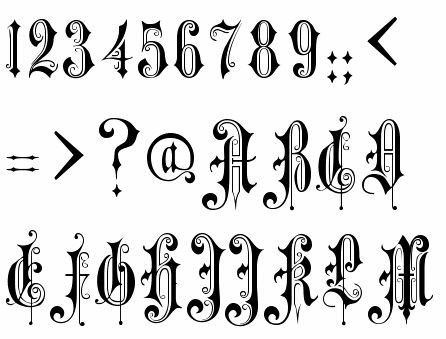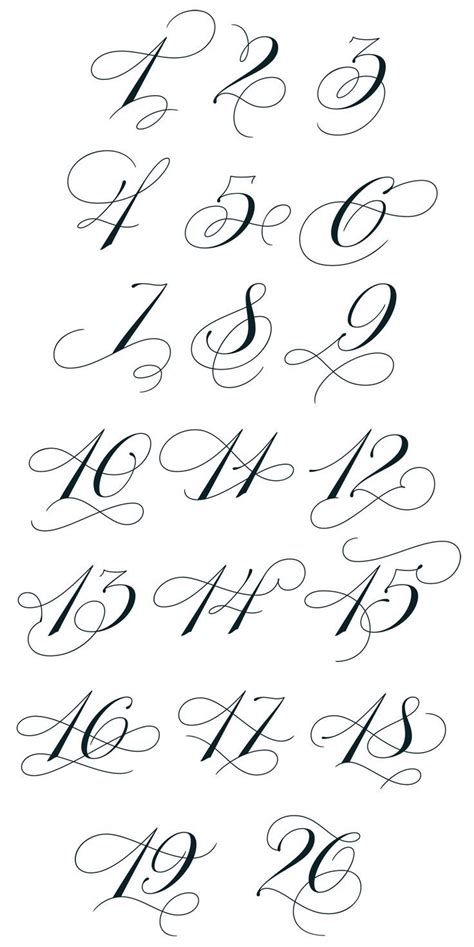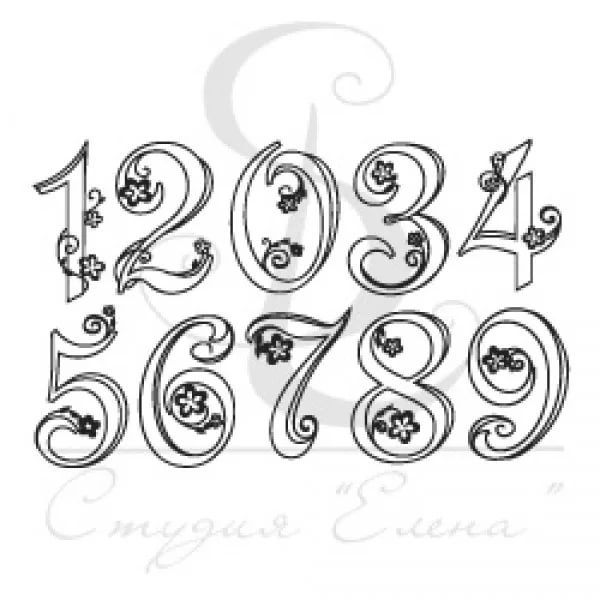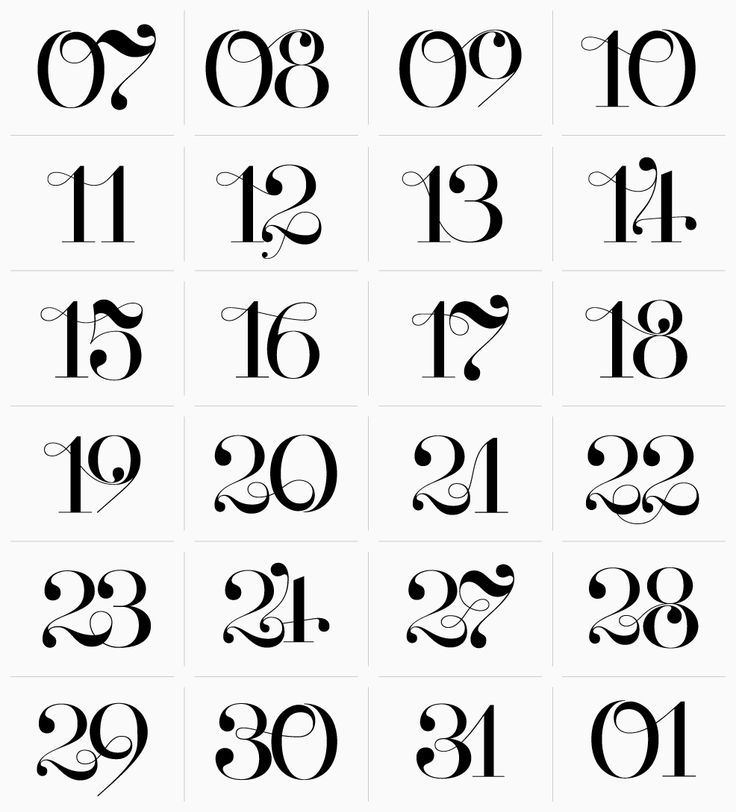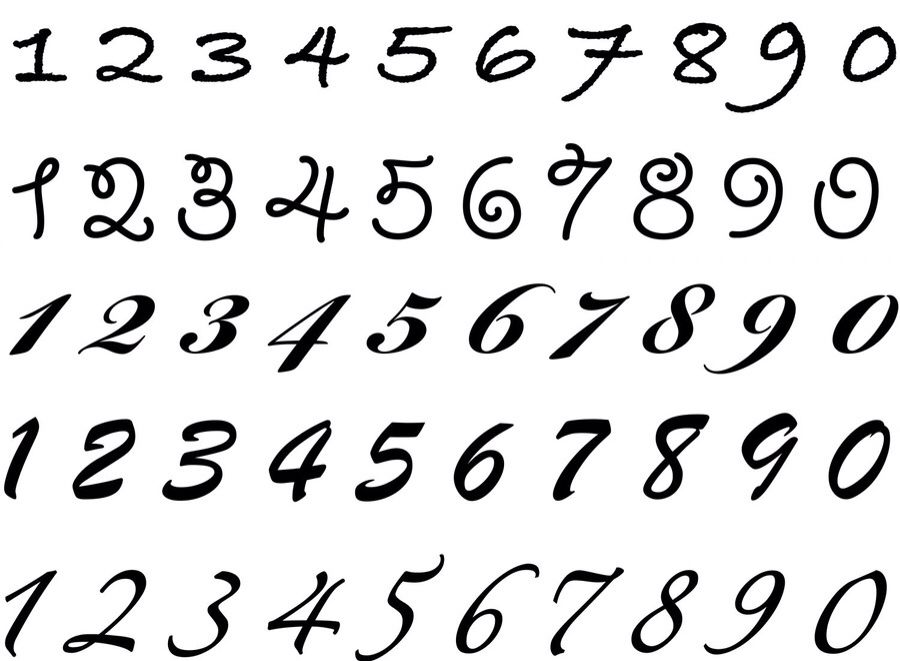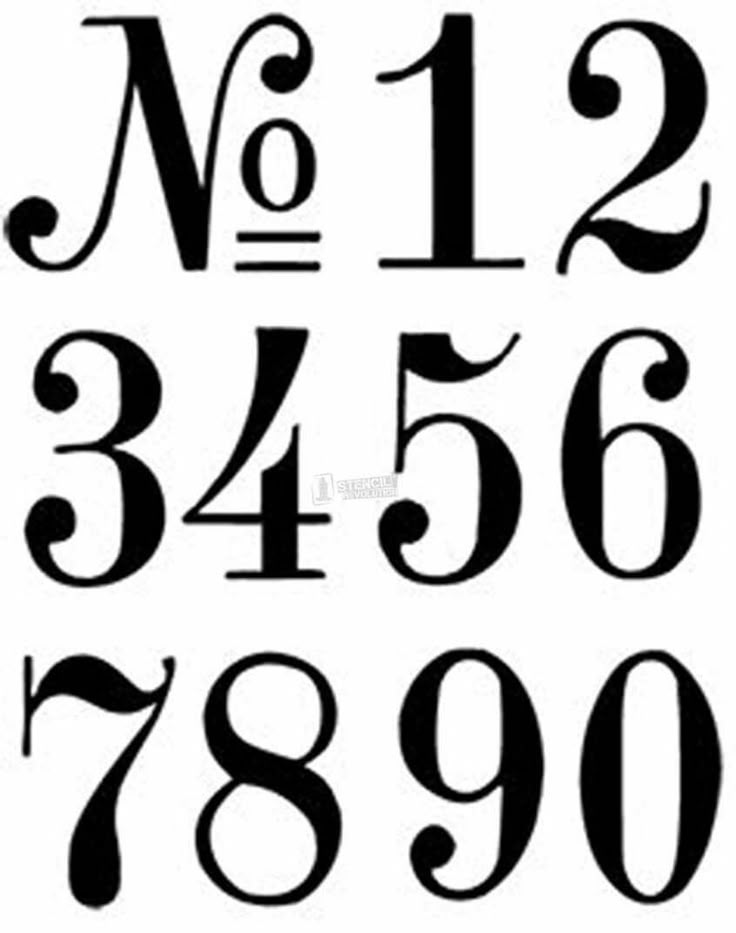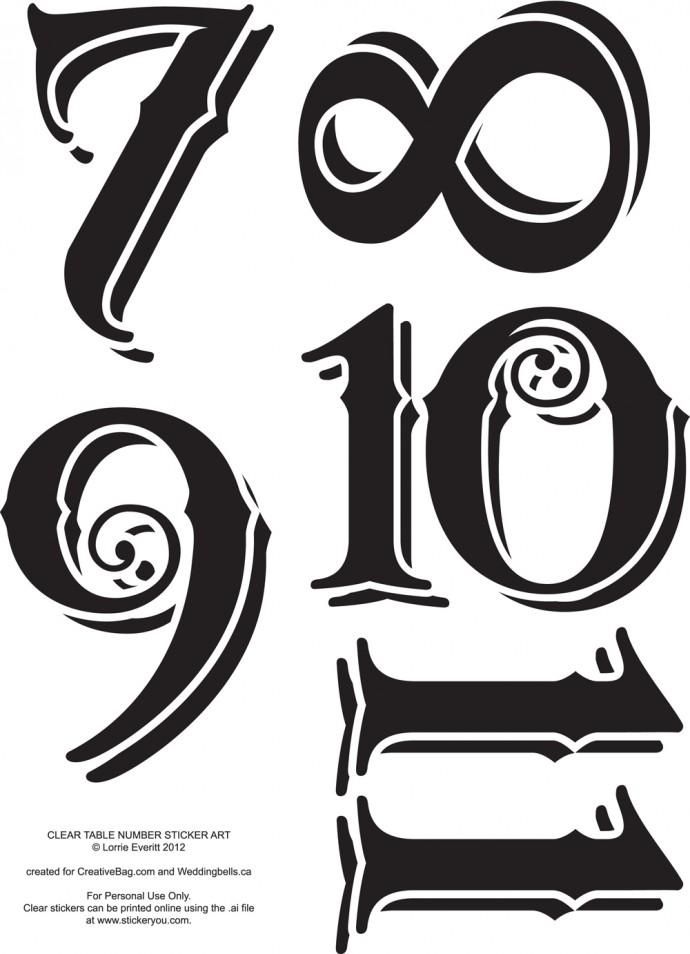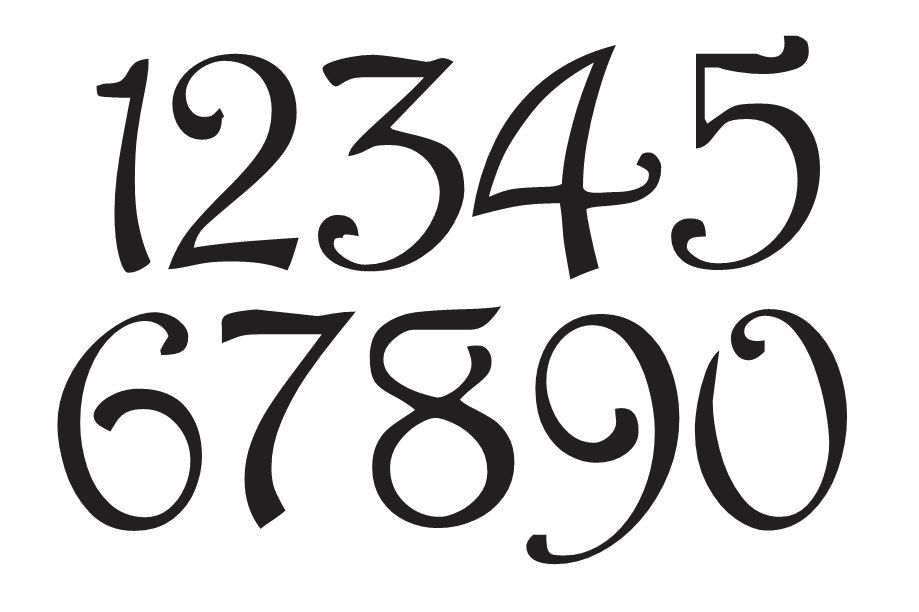
Сегодня я завершу рассказ о фичах. Этот совет — про цифры, альтернативные знаки и стилистические сеты.
В прошлом совете я разбирала принцип позиционирования и замены знаков. И цифры, и альтернативные знаки, и стилистические сеты действуют по принципу замены знаков. С такими фичами мы можем менять форму знаков или цифр.
Цифры
Во многих шрифтах есть несколько наборов цифр для разных задач: табличные (моноширинные), минускульные (старостильные), маюскульные (основные), минускульные табличные.
Обычно самые стандартные цифры — маюскульные, то есть размером с прописные знаки. Их можно заменить на табличные или моноширинные — рисунок останется тем же, но выравнивается ширина каждой цифры. Табличные цифры идеальны для таблиц — при большом количестве чисел искать нужное число удобнее, когда все цифры стоят в ряд друг под другом:
Если цифр в таблице много, и часто нужно находить определённые числа, то моноширинные табличные цифры подойдут лучше всего.
Минускульные цифры чаще всего встречаются в антиквах, потому что они хорошо смотрятся в строке в большом наборе текста.
Минускульные цифры ровняются по высоте строчных знаков и имеют выносные элементы. Шрифт Бюросериф
Но в гротесках они тоже часто есть, и иногда они могут играть красивую завлекающую роль:
Обложки журнала «Московское наследие» 2013 года. Минускульные цифры в заголовках набраны шрифтом Цирцея
Минускульные цифры тоже могут быть моноширинными, если такая фича доступна в шрифте.
В Цирцее есть и моноширинные минускульные цифры
Альтернативные знаки
Альтернативные знаки — это другой рисунок буквы. Обычно нужны для достижения определённого визуального эффекта.
Альтернативные знаки условно делятся на контекстные и стилистические. Контекстные альтернативы работают в неудачных соединениях букв для лучшей считываемости.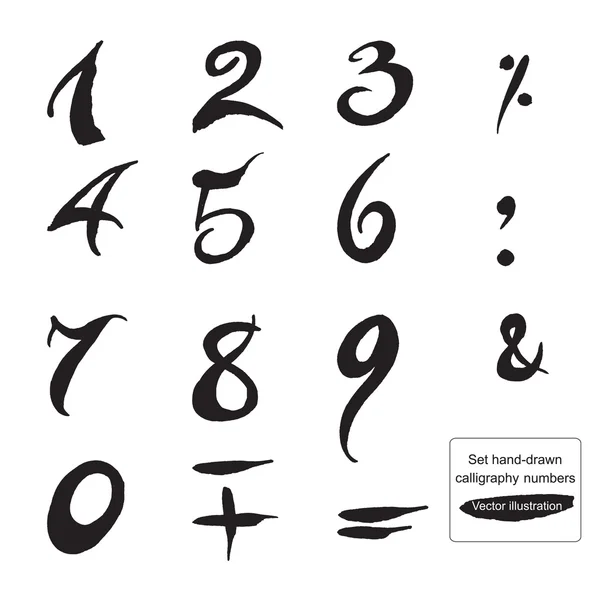
Слева двучастные «a» и «g» — состоящие из двух частей. Эти же буквы, но одночастные — стилистические альтернативные знаки. Шрифт Искра
Альтернативные знаки хорошо работают в разных акцидентных шрифтах.
Шрифт Интерлок компании «Хаус Индастрис». Его принцип схож с вязью, где каждый глиф подстраивается в ряд к другим. Глифы работают по принципу лигатур, но являются при этом альтернативными знаками. На сайте можно тестировать набор и смотреть, как ведут себя буквы. Как жаль, что нет кириллицы
Также в альтернативные знаки входят и росчерки — каллиграфические элементы в глифе.
В одном из моих любимых шрифтов Амальта красивые начальные и концевые росчерки
Стилистические сеты
Стилистические сеты — это продуманные шрифтовым дизайнером готовые наборы альтернативных знаков для достижения определённого эффекта.
Например, в шрифте Цирцея есть целых 11 стилистических сетов. В каждом из них определённые глифы заменяются на альтернативные.
Стилистический сет № 1 в Цирцее. Подробнее о стилистических сетах и остальных фичах шрифта можно прочитать в ЖЖ шрифтовой компании «Паратайп». Картинка оттуда же
Я советую обращать внимание на такие сеты, потому что они здорово могут украсить и оживить набор.
Иногда стилистические сеты сделаны специально, если пользователю понадобится добавить определённый характер в набор. Например, исторический.
У шрифта Казимир компании «Тайп тудей» есть стилистический сет под названием Irregular. У него «состаренные» знаки, которые хорошо работают в акциденции.
Картинка из ПДФ шрифта с сайта компании
Фичи — это не просто дополнительные плюшки к шрифту, а инструмент, которым можно и нужно пользоваться по необходимости. Обычно фичи показаны сразу на странице шрифта. На некоторых сайтах, например, на сайте Майфонтс, можно настроить поиск по нужным фичам. Рекомендую изучать набор фич в шрифте прежде, чем покупать шрифт.
Шрифты
Определение шрифтов, которые применяются для элементов формул.
Доступ к этой команде
Последовательно выберите команды Формат — Шрифты.
Шрифты формул
Можно определить шрифты для таких элементов формул, как переменные, функции, числа и вставляемый текст.
В списках диалогового окна Шрифт для всех элементов отображается шрифт, заданный по умолчанию. Чтобы изменить шрифт, нажмите кнопку Изменить и выберите тип элементов. Отображается новое диалоговое окно.
Выберите необходимый шрифт и установите требуемые атрибуты, а затем нажмите кнопку OK. Чтобы внесённые изменения использовались по умолчанию, нажмите кнопку По умолчанию.
Если требуется установить для определённых текстовых сегментов шрифт, отличный от используемого для всего текста, введите команду FONT в окне Команды.
Переменные
Можно установить шрифты, используемые в формуле для переменных. Например, в формуле x=SIN(y) переменными являются «x» и «y», они будут отображаться с использованием назначенного шрифта.
- Оригинальный шрифт Burger (для дизайна в стиле ресторана и кафе)
Как дизайнер, вы должны помнить, что удобочитаемость чисел имеет решающее значение. Наш разум приучен быстро читать буквы и формировать из них слова и предложения, но когда дело доходит до чисел, ошибка в понимании может привести ко многим серьезным проблемам. Ниже приведены некоторые из самых простых шрифтов для чтения чисел:
- ПРОСТО Санс
- Числа Клемента
- Омикрон
- Ретрофутуризм
Хороший математический шрифт отображает все числа, символы и формулы легко и разборчиво.